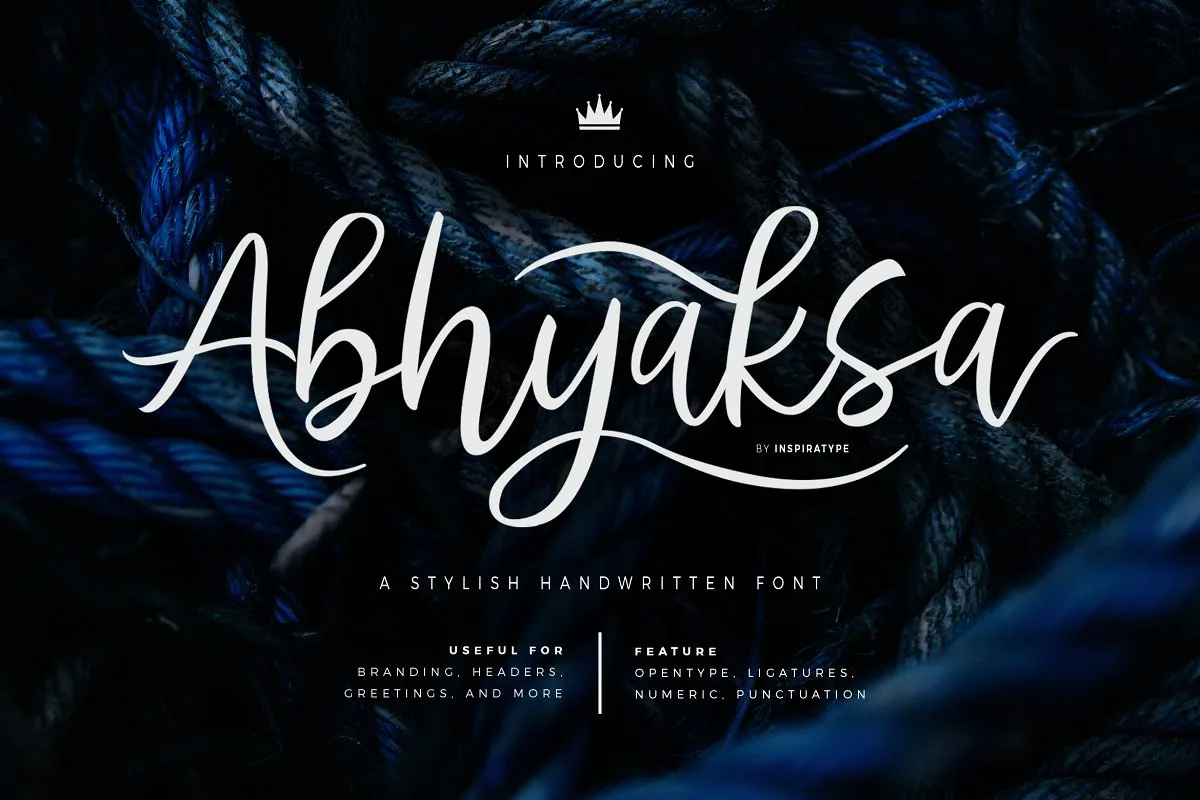
Abhyaksa Handwritten Font – Download Grátis
A fonte Abhyaksa é uma opção perfeita para quem busca algo charmoso e versátil. Inspirada nos clássicos posters, a Abhyaksa é um estilo de letra a mão, ideal para dar vida à suas criações digitais. Esta font contém uma gama completa que inclui letras maiúsculas e minúsculas, números e vários tipos de pontuação. Ela também oferece alternativas do OpenType e ligaturas comuns para tornar os teus designs ainda mais personalizados. A Abhyaksa é uma excelente escolha para diversos aplicativos, como logotipos, cartões de visitas, outdoors, design de roupas e etiquetas. A sua versatilidade permite que esteja sempre a crescer e adaptar-se à tua necessidade criativa. Ideal tanto para designers profissionais quanto para aqueles que apenas querem tornar-se mais experientes no uso da fonte. Como uma font script, a Abhyaksa é perfeita para quem deseja adicionar um toque autêntico e elegante aos seus projetos digitais.